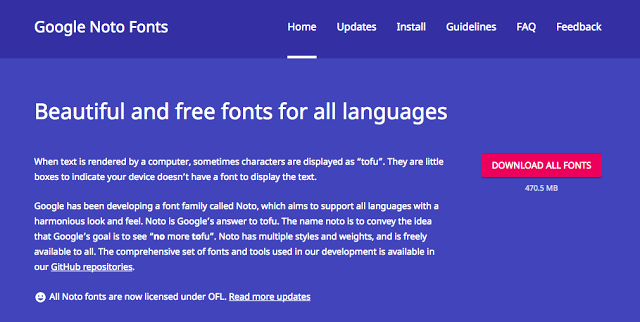
五年前開始, Google 展開了設計全世界各種語言字型的計畫,一開始的目的是讓 Android 與 Chrome OS 等系統能夠具備完整的多語字型支援,讓每種語言的字型有設計上的一致性,無論在顯示網頁、展示介面、閱讀文書時都「不會出現無法顯示的豆腐方塊」。
所以叫做「 no more tofu 」,簡稱為「 Noto 」,亦稱為「 Google Noto Fonts 」。
其中針對每種特殊語言的字型支援,則是與各種志願者和不同單位合作開發, Google 則提供設計的統一風格指導,例如兩年前在台灣轟動一時的免費中文字型:「Adobe與Google合推全新中文免費字型思源黑體」,正是這個計畫中的一支。
而時至今日(2016/10/7), Google 正式宣佈 Google Noto Fonts 的開發達到一個里程碑,全面支援所有 Unicode 編碼字元,擁有支援 800 種語言的字型,也包含一些特殊符號,總計有 11 萬個字符。並且 Google 承諾未來會隨著新增的字符繼續擴充。